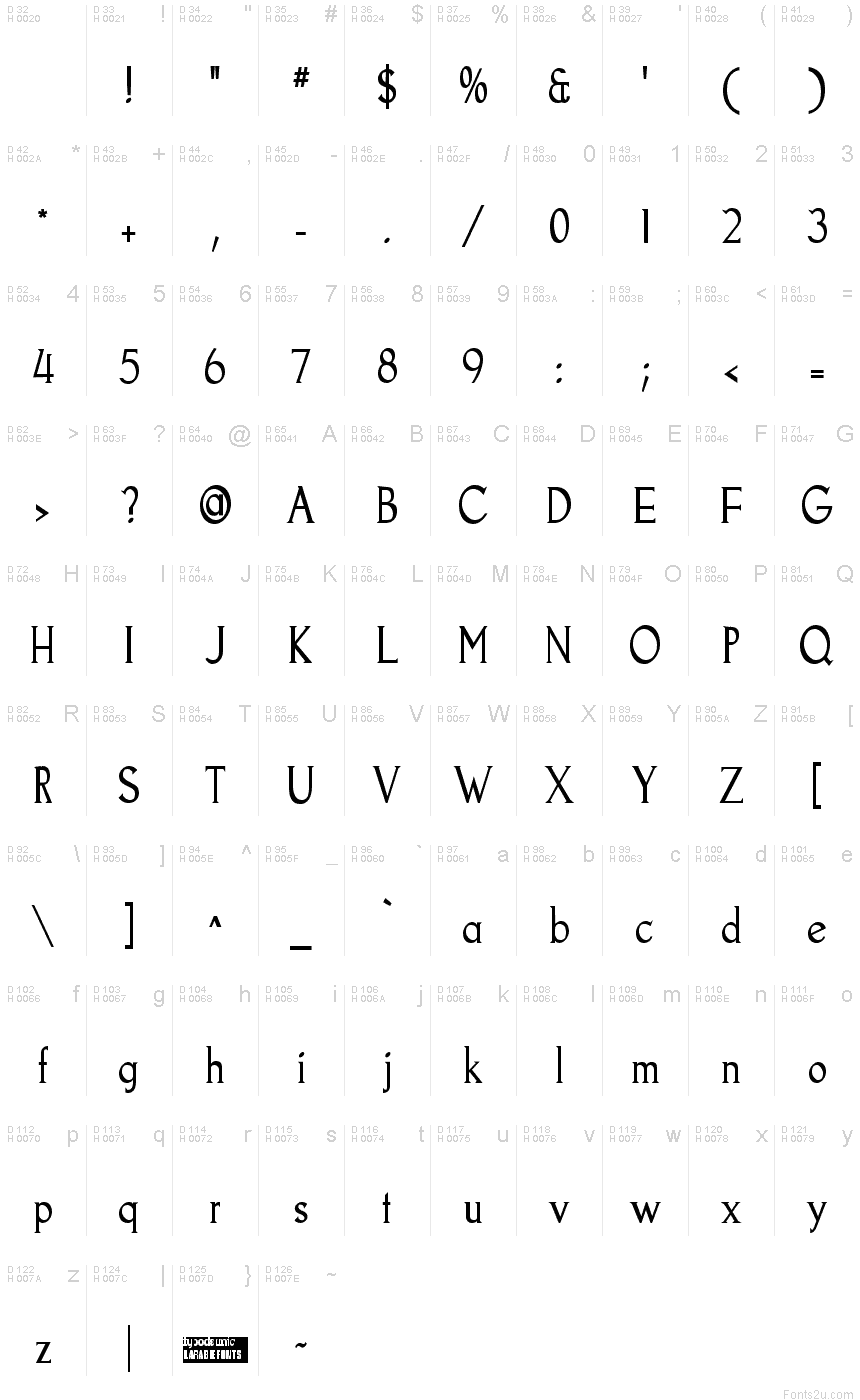
Goodfish autorstwa Raya Larabie to darmowy, dekoracyjny krój szeryfowy o cudownie ekscentrycznym uroku. Litery balansują między dużymi, zaokrąglonymi brzuszkami a iglastymi szeryfami, przypominając tytuły ze starych baśni z nutką tajemniczości. Pociągnięcia sprawiają wrażenie rysowanych tuszem i ręcznie wycinanych, co nadaje nagłówkom namacalny, papierowy charakter, zamiast typowego cyfrowego wygładzenia.
Dzięki Goodfish Twoje nagłówki natychmiast zyskują charakter – stają się kapryśne, lekko gotyckie i niepowtarzalne. Ten darmowy font świetnie sprawdzi się na okładkach książek, plakatach fantasy lub kryminałów, w tytułach gier, grafikach na Halloween, niszowych logotypach marek i opakowaniach w stylu retro. Spróbuj zestawić Goodfish z czystym, geometrycznym krojem bezszeryfowym w mniejszych rozmiarach, aby zachować czytelność, jednocześnie pozwalając wyrazistym, ostrym formom Goodfish grać pierwsze skrzypce.